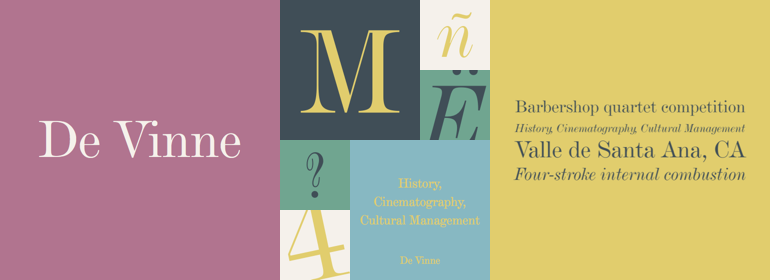
De Vinne
De Vinne,这款字体结构工整、笔画清晰,兼顾美观与易读性,适用于标题、正文、海报、包装、LOGO 等多种场景。字形优雅稳定,风格百搭耐看,适配日常排版与创意设计,让文字呈现更舒适、更具质感。De Vinne一笔一画,皆是细节,以均衡的比例、流畅的线条打造舒适视觉体验,字形端正大气,风格简约现代。无论是商业设计、品牌宣传还是日常排版,都能轻松驾驭,让文字更有格调与力量。De Vinne字体下载。
字体品牌: Bitstream(Monotype) 设计师:Schroeder,Gustav F. 字体分类:衬线体 字体属性:外文 字符集:Unicode 发布时间: 2018